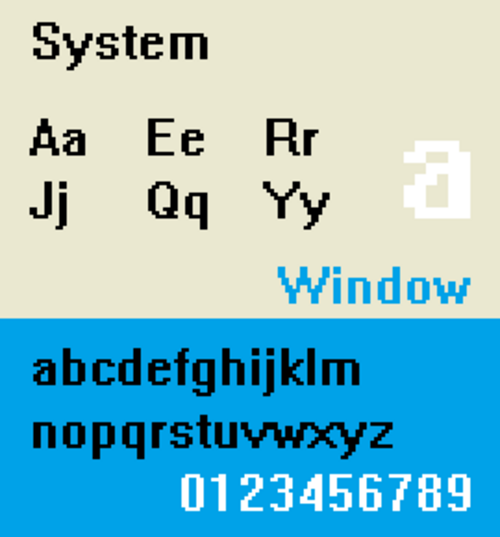
| カテゴリ | サンセリフ |
| デザイナー | マイクロソフト |
| 鋳造所 | マイクロソフト |
| 作成日 | 1988年 |
System は、Microsoft Windowsに同梱されているプロポーショナルラスター フォントのファミリです。[1] Microsoft Sans Serifと同じ字形 ( Helvetica をモデルにしています)を共有するこのフォント ファミリには、複数の Windowsコード ページでエンコードされたフォントが含まれており、コード ページごとにフォントの解像度が複数あります。コード ページが異なると、フォントのポイント サイズも異なります。2バイト文字セットのWindows 環境では、このフォントを指定すると、アプリケーションがテキストを表示するときに System 以外のフォントを使用することもあります。
Windows 2000以降では、一部のアプリケーション (メモ帳、ワードパッドなど) のフォント ダイアログでスクリプト設定を変更すると、同じフォント サイズであってもフォントの外観がまったく変わります。同様に、Unicode をサポートしていない Windows アプリケーションの言語設定を変更すると、フォントの外観が変わります。
Windows がシステム リソースが少ない状態で実行されている場合、System はテキストの表示に使用されるフォールバック フォントです。
.FON ファイル内の著作権メッセージには、このフォントが 1988 ~ 1989 年に Microsoft Corporation によって設計されたと記載されています。
Microsoft は、フォントの CGA、EGA、8514/Aバージョンも作成しました。8514 バリアントは、高 DPI バージョンとして、Windows 10 や 11 バージョンなどの最新の Windows バージョンで引き続き使用されています。
Bitstream からビットマップ フォントのライセンスを取得しましたが、それらに大幅な変更を加えました。最初の Windows ユーザー インターフェイス フォントは、Windows 1 に付属していた固定ピッチ ビットマップ フォントの「SysFixed」でした。Windows 2 では、プロポーショナル ビットマップ フォント「System」のサポートが追加されました。